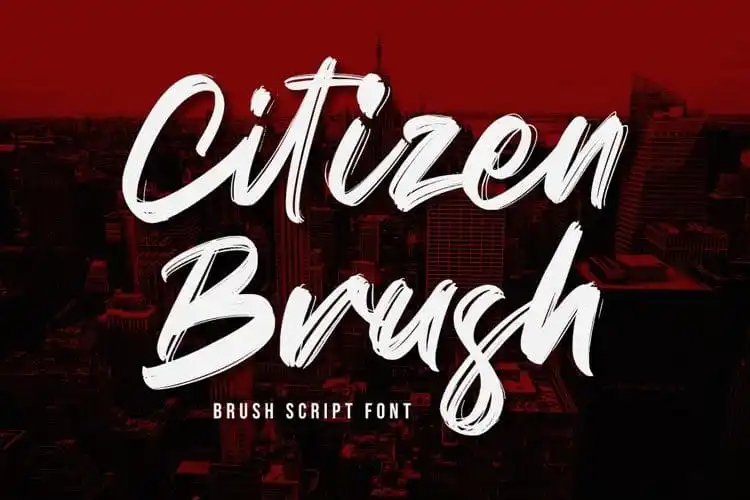
Citizen Brush Font – Download Grátis
Aqui está uma versão em português do Brasil para a descrição solicitada sobre a fonte “Citizen Brush Font”: “Descubra a fonte ‘Citizen Brush Font’ neste download, um estilo de letra criado pela Fatma Studio, que traz uma sensação relaxada e deslizante de escrita manual. Esta é uma fonte script fluida perfeita para projetos pessoais e corporativos. Com seus traços elegantes e suas linhas fluidas que se misturam com um toque suave, esta fonte tem um aspecto único e imortante que combina bem em diversos tipos de projetos. Da criação de cartões de boas-vindas aos títulos dos trabalhos, do design de escritório à personalização de produtos de papelaria. Seja apaixonado por seu estilo distintivo e eterno, ‘Citizen Brush Font’ pode ser a fonte perfeita para dar um toque especial às suas criações. Transformá-las em designs impressionantes que se destaquem do resto.” Esta descrição mantém o tom informativo e convidativo pedidos, sem repetir o nome da fonte ao longo de todas as frases, enquanto transmite a essência e os benefícios da fonte de forma clara e envolvente.